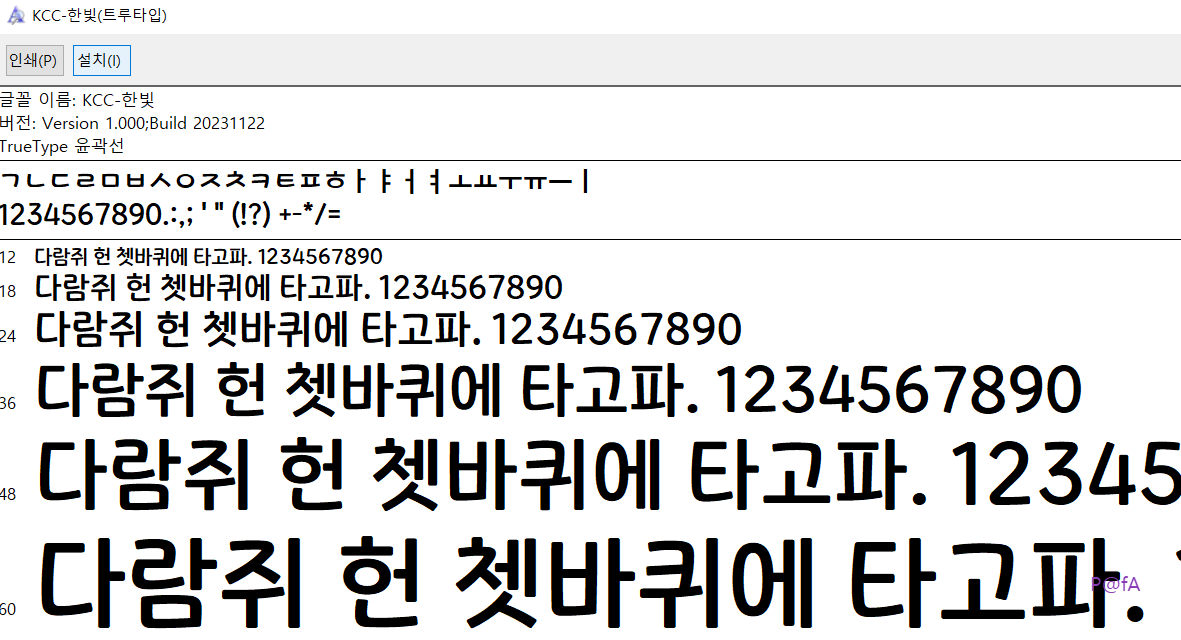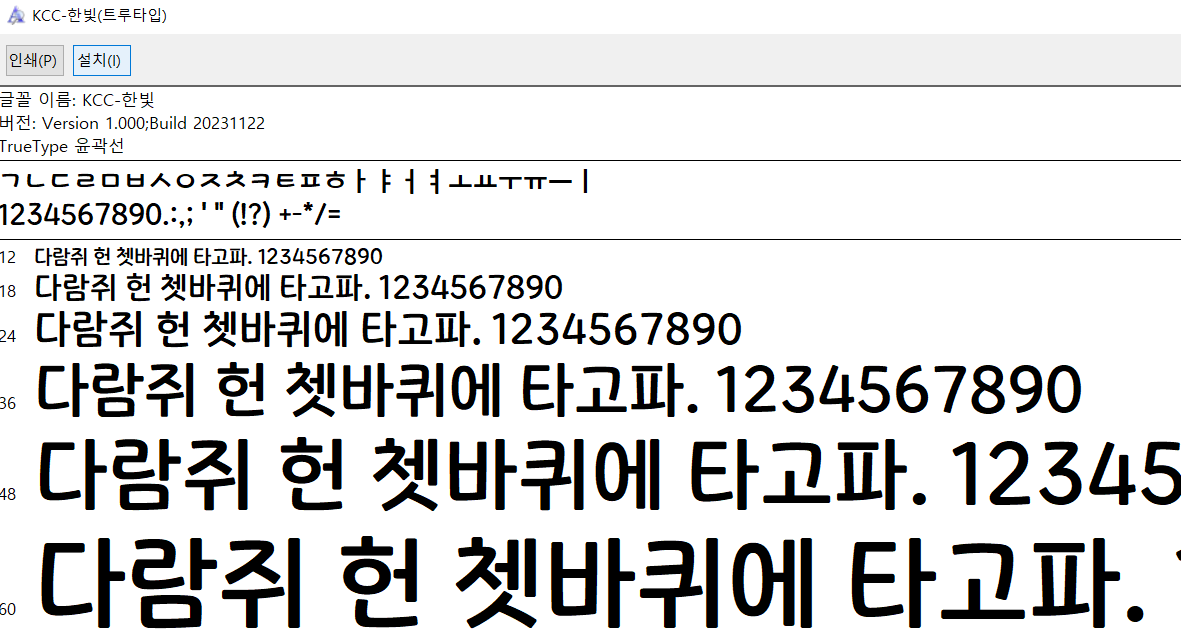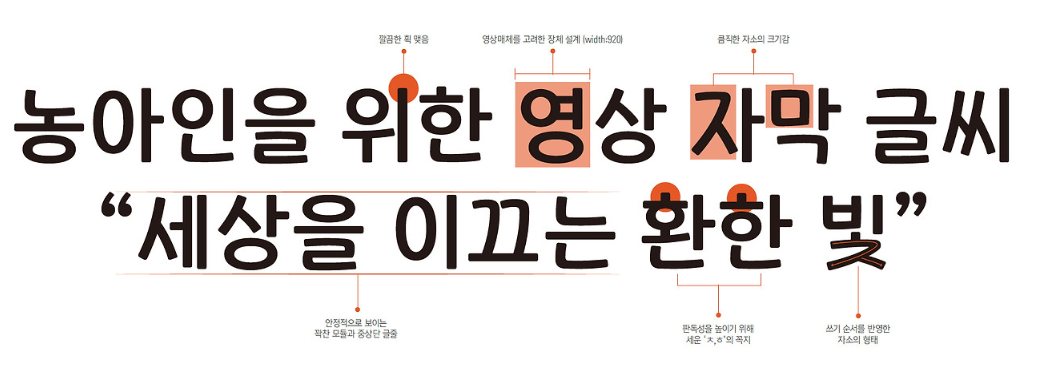
청각장애인을 위해 제작된 최초의 글꼴로 알려진 KCC한빛체는 문화체육관광부와 한국저작권위원회에서 청각장애인을 위한 영상 자막용 손글씨 폰트로 개발해서 무료로 제공하고 있다. 다음에서 해당 KCC한빛체를 무료로 다운로드하는 방법과 더불어 컴퓨터에 설치하거나 코딩 시에 사용하는 방법도 살펴본다.
청각장애인을 위한 영상 자막용 폰트 KCC한빛체 무료 다운로드
누구나 개인적인 용도뿐만 아니라 상업적인 용도에도 무료로 사용할 수 있도록 제공하는 무료 폰트인 KCC한빛체를 소개한다. 2024년에 출시된 KCC한빛체는 한글 11,172자를 비롯해서 라틴 95자, KS기호문자 925자 그리고 수어 딩벳 61자로 구성되어 있는 글꼴이다. 다음에서 제시하는 순서대로 따라 하면 KCC한빛체를 무료로 다운로드해서 사용할 수 있다.